השאלון עם אדם קנת
הכירו את אדם קנת, יליד מרץ 1995 ״שבסין זו שנת החזיר״, הוא מדגיש. אדם חי בתל־אביב עד שלפני כחצי שנה עבר לליסבון. בקיץ 2023 סיים את לימודיו במחלקה לתקשורת חזותית בשנקר – חוויה שהוא מתאר כסוחפת, קשה ונפלאה. לאורך הדרך עבד בסוגי משרות מגוונות, ביניהן כשנה כ"אפטריסט" בסטודיו פרומותאוס. אדם עוסק בטיפוגרפיה, מיתוג ומושן דיזיין, אך מוצא עניין גם בתחומי עיצוב נוספים. הוא מתחבר במיוחד לעיצוב שמוקפד עד רמת הפרטים הקטנים – כזה שבו כל ניואנס נעשה מתוך מחשבה, גם אם אינטואיטיבית או בטעות. מלבד עיצוב, הוא חי מוזיקה ומנגן, אוהב לטייל בטבע ובכלל, לאכול טוב, לעשות ולצפות בספורט, ואוהב חיות מכל הסוגים (חוץ מיתושים). בגדול, הוא בעד לחוות כמה שיותר מהחיים הקצרים.
זה מאוד תלוי בסוג הפרויקט, אבל כשמדובר בלטרינג וטיפוגרפיה, אני בדרך כלל מעדיף לעבוד לבד.
על איזה פרויקט מעניין עבדת לאחרונה?
ממש בימים האלה אני מסיים ליצור מושן ברנד־בוק עב־כרס לחברה שמטפלת בסרטן.
אני אוהב שיש לי סיבה ליצור – משימה שמניעה אותי. גם אם הפרויקט רחוק מאזור הנוחות שלי, ברגע שלקחתי אותו על עצמי הוא הופך לשלי, ואני נכנס אליו בכל הכוח, מאוד משימתי.
מה אתה עושה כשאין לך מוזה?
אם אני מתיישב לעבוד ומרגיש מרוקן ממחשבה יצירתית, אני לוקח הפסקה – כמה שצריך, אפילו לכמה שעות או יום, אם זה מתאפשר.
מה משך אותך לתחום?
גדלתי בבית אמנותי ותמיד הייתי מצייר ומעצב. עדיין, לקח לי הרבה שנים להפנים שיש לי עין עיצובית טובה ויצירתית. אני חושב שקרתה אצלי איזו קפיצה בהבנה הזו תוך כדי בניית תיק העבודות לשנקר, קלטתי שיש אצלי משהו בראש ששווה בדיקה יותר מעמיקה.
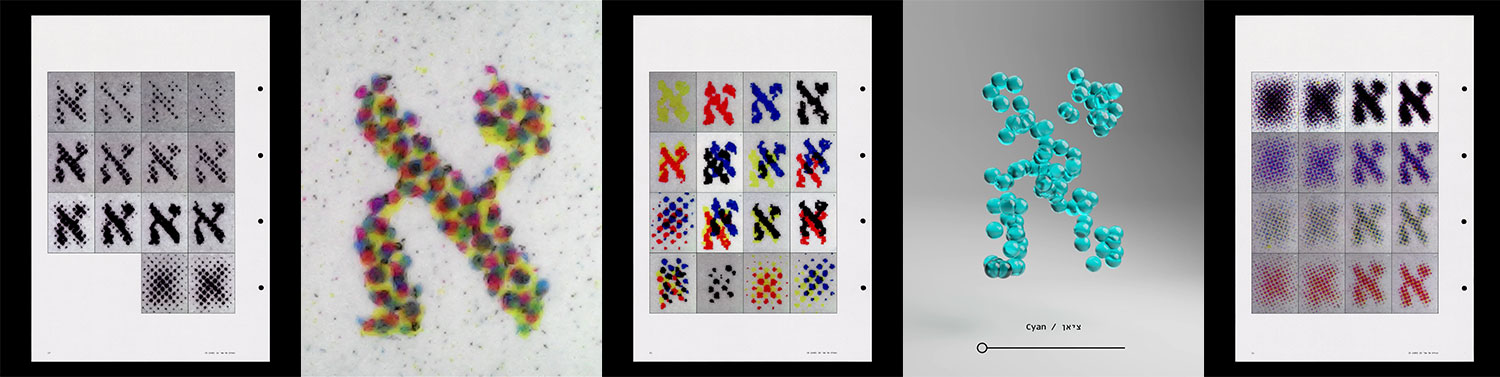
עבודתו של אדם קנת, ״אָלֶף 600״, היא פרויקט מחקר טיפוגרפי־עיצובי העוסק בצורתה של האות הראשונה באלפבית העברי – א – כאשר היא נבחנת דרך מיקרוסקופ דיגיטלי בהגדלה של פי 1600. במהלך הפרויקט הודפסה האות בגודל זעיר של 7pt על גבי סוגי נייר שונים ובשיטות דפוס מגוונות, וצולמה כתקריב דרך עין המיקרוסקופ. אדם מספר כי "מקרוב, צורת האות המוגדלת התפרקה לחלקיה (CMYK), כאשר הצבע האחיד שלה התפוגג ליסודותיו". המחקר המשיך לכדי מניפולציות נוספות, שכללו צילום חוזר של התקריבים, דיגיטציה וקטורית שלהם ובחינתם במרחב תלת־ממדי. דרך הפרויקט נבחנה יכולתה של צורת אות פשוטה לשאת בתוכה עומק חזותי וטכנולוגי מורכב.
איזה מרצה השפיע/ה עליך במיוחד?
אני לא חושב שיש מרצה שהשפיע/ה עליי יותר מכולם. אביגיל ריינר פתחה לי את הצ׳אקרה לפורמט מדופדף, מושון זר־אביב איפשר לי להבין שאין כזה דבר מושלם בעיצוב וגם לאפל וגוגל יש לאן להשתפר, עידן אפשטיין שלימד על תהליכי עבודה בעולם המיתוג, קובי פרנקו עזר לי למצוא שפה משל עצמי, דקל מימון שגם הנחה אותי בפרויקט הגמר. ויש עוד.
איזה מעצב/ת השפיע/ה עליך יותר מכל?
באיזה פונט אתה רוצה שיכתבו על המצבה שלך?
הממ… חושב שהייתי הולך על פרנק־ריהל.
״אני אחר״ הוא ספר שעיצב אדם קנת במסגרת קורס "תוכן מורכב", בהנחיית ניר ייני. הספר מחולק לשני חלקים ונוגע במגוון רחב של פרשנויות למושג "אלטר־אגו". דרך סיפורי חיים, ראיונות וכתיבה מקורית, מציג הפרויקט זוויות שונות של זהות כפולה — החל מגיבורי־על ודמויות ספרותיות, ועד למוזיקאים, מלכות דראג וסוכנים חשאיים. הספר עוסק במתח שבין דמות לאדם, ומציע לקוראת ולקורא התבוננות פנימית על המקום שבו הזהות נזילה, חמקמקה, ולעיתים גם מומצאת.
איך עולם העיצוב ייראה בעוד עשור?
אני מניח שהגבול בין אדם למכונה ימשיך להטשטש ונאלץ לאמץ את זה, לטוב ולרע.
זה לא בדיוק שם חיבה כמו פשוט שם שני שהוא הזייה: קיילו (Kylou). כן, גם בת.ז.
קיצור מקלדת אהוב
Cmd+S, יור וולקאם.
כתוב בבקשה את המילה הבאה בכתב היד שלך: